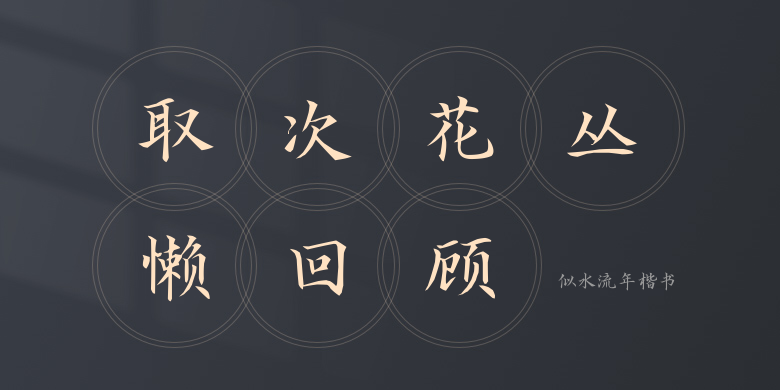
似水流年楷书
似水流年楷书,这款字体结构工整、笔画清晰,兼顾美观与易读性,适用于标题、正文、海报、包装、LOGO 等多种场景。字形优雅稳定,风格百搭耐看,适配日常排版与创意设计,让文字呈现更舒适、更具质感。似水流年楷书一笔一画,皆是细节,以均衡的比例、流畅的线条打造舒适视觉体验,字形端正大气,风格简约现代。无论是商业设计、品牌宣传还是日常排版,都能轻松驾驭,让文字更有格调与力量。似水流年楷书字体下载。